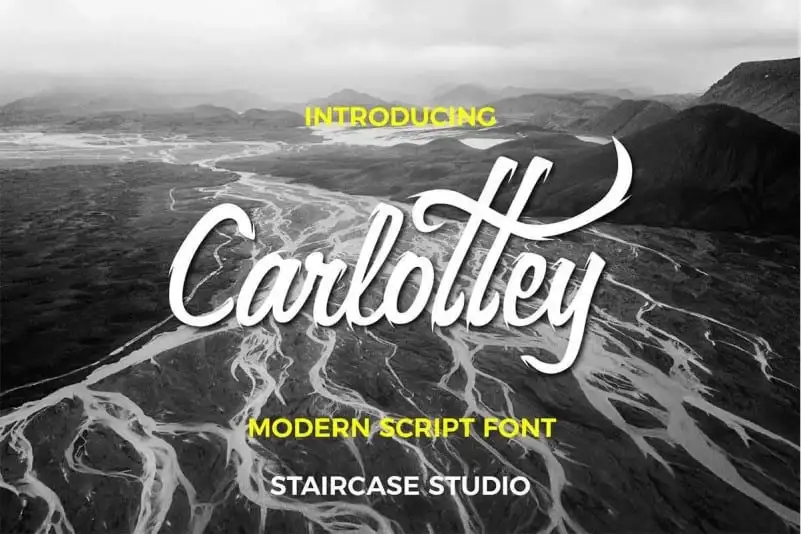
Carlottey Calligraphy Font – Fonte Grátis
Carlottey Calligraphy Font
Introduzimos a Fonte de Calligrafia Charlottey. É elegante, feminino e sofisticado ao mesmo tempo. Seu estilo é moderno e femenino, criada pelo designer Staircase Studio. Carlottey tem um encanto especial e sofisticação única. Este conjunto de letras e números é perfeito para diversos projetos – seja o seu logotipo, design da marca, arte de logo, letra digital, t-shirts ou roupas, cartazes, revistas, sinalização ou publicidade. Carlottey é uma fonte elegante para qualquer necessidade de design. Acompanhe seu site para mais detalhes e modelos ilustrativos desta fonte única.